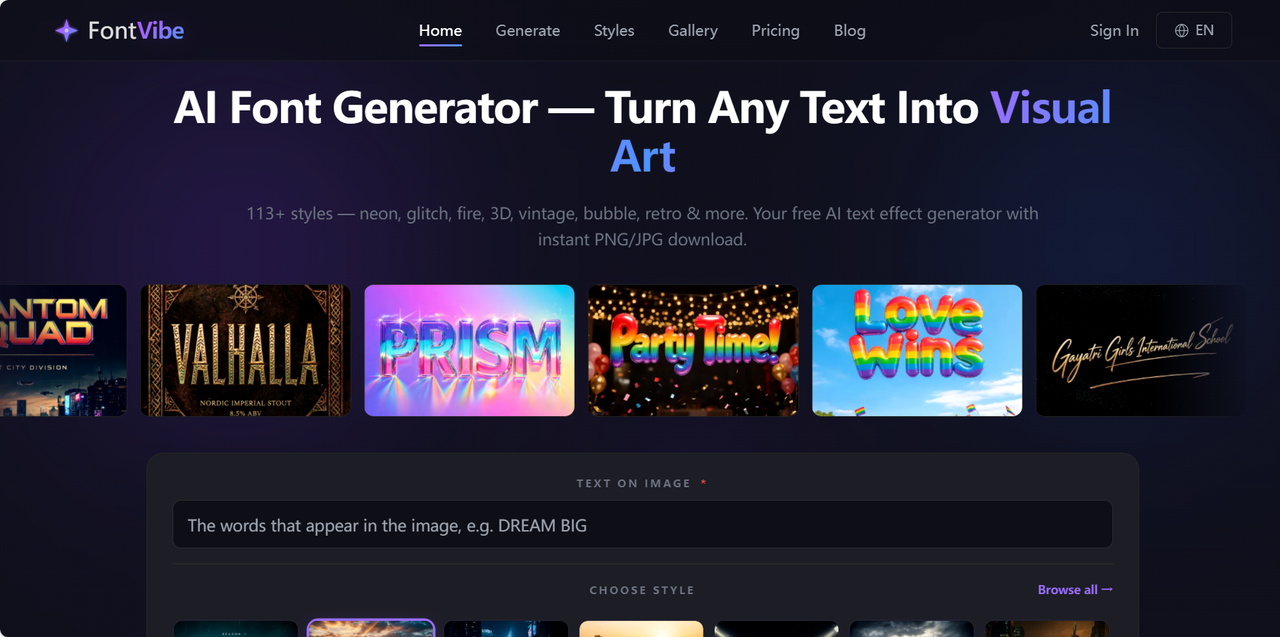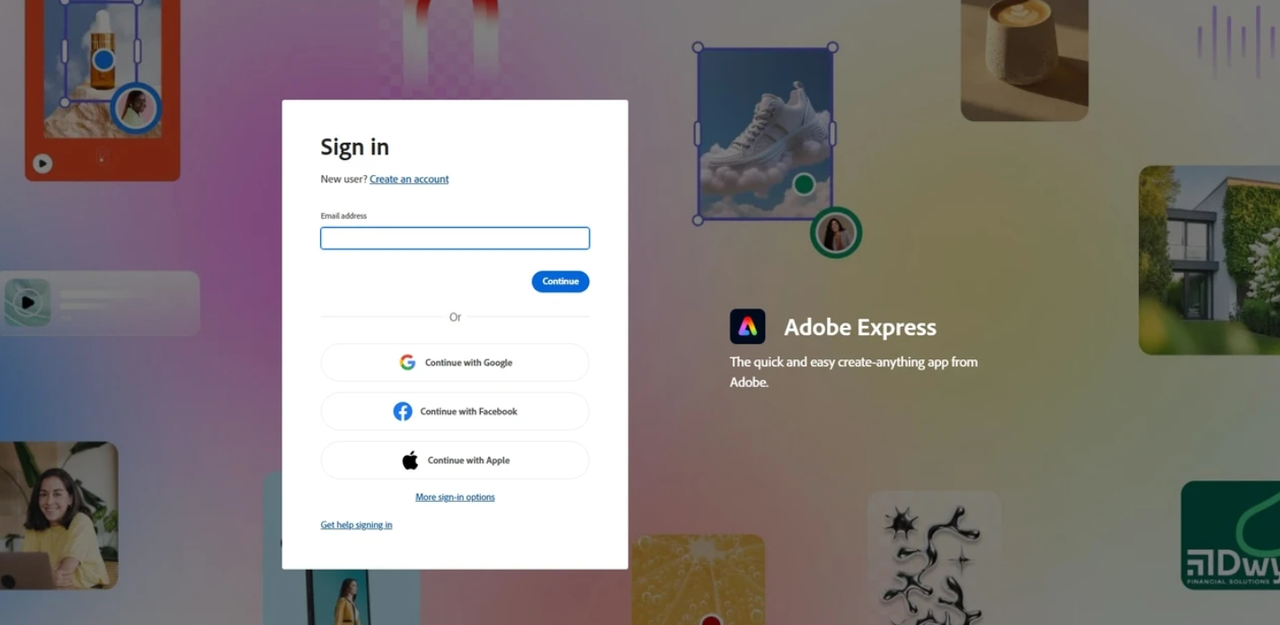
文字变艺术字怎么转?艺术字转换器大汇总
觉得自己选择的字体太过普通,想要把普通文字变成艺术字却不会用 Photoshop?别慌!如今市面上有不少好用的艺术字转换工具,无需设计基础,选择模板就可一键出图,完美适配海报、品牌、短视频封面、社交媒体配图等设计场景。艺术字不仅美观有趣、醒目张扬,而且用途广泛,选择一款适配的艺术字能一秒抓住观众的眼球。本文整理了 5 个优质的艺术字转换器,全程傻瓜式操作,帮你快速搞定各种创意艺术字需求,让文字瞬间出彩,让你的设计作品更加光彩夺目!
一、字由
字由是目前国内规模较大的字体管理工具,注册用户远超 2000 万,与汉仪字库、蒙纳字库等字体厂商有深度合作,同时作为腾讯、京东、小红书、国家电网、华为等国内头部大品牌合作伙伴,产品值得信赖。字由拥有海量字体资源,其中免费商用字体 3590+ 款,会员商用字体 590+ 款,授权方式灵活,满足多样化设计需求。用户只需要选择自己喜欢的艺术字资源,输入自定义文本内容,即可在线预览字体效果,实现普通文字到艺术字的转换。字由还在字体使用这方面进行了流程优化,通过字由客户端可实现在 PS、AI、ID、XD、Figma、Sketch、CDR 等设计软件中一键应用字体,无需下载安装字体包,即可完成字体应用。如果你觉得这些还不能满足你的需求,字由还提供 400+ 字体特效目标,包含电商,商务,科技感,新媒体等各类风格,用户可对特效文案,文字效果进行自定义编辑,打造一个更吸睛的艺术字效果,编辑后一键导出 PNG 图片,即可应用于作品中。
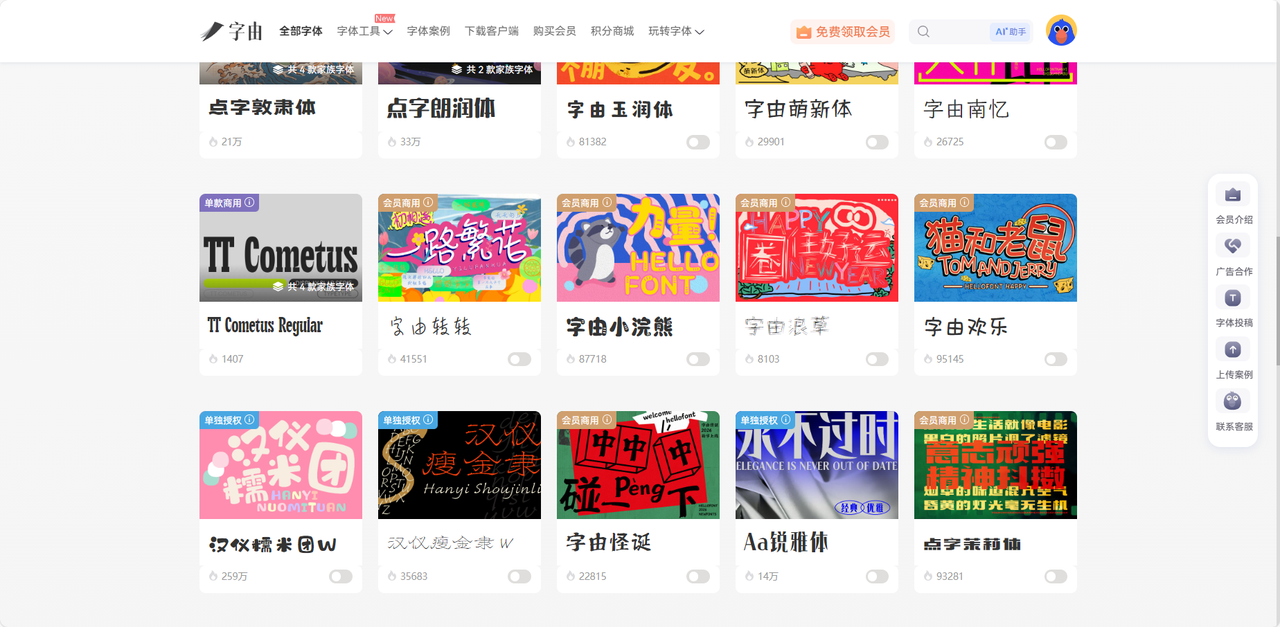
二、FontVibe
FontVibe 主要是给字体添加风格特效,比如霓虹、故障、火焰、赛博朋克等 100 多种文字视觉效果,让你的艺术字变得更加有视觉冲击力。操作流程非常简单,用户在输入框中输入自定义文案内容,从各种风格中挑选一个自己想要的,AI 会即刻完成自动渲染,导出高清或透明背景的 PNG 图片可直接用于其他设计软件。就整体的视觉效果来看,FontVibe 对于艺术字风格的质感控制相当智能,它不是单纯的在笔画边缘叠加一层光环,而是通过内置的 AI 系统将文字、光影、材质等细节完美适配,会让字体的呈现效果更加真实生动。
最近 FontVibe 还上线了一个新的字体风格,就是花卉植物类风格,也就是说你只需要输入一个名字,它会自动将植物元素(比如玫瑰、牡丹等)融入字体笔画内部,非常适合用来制作婚礼请柬、母亲节卡片、手作店品牌等,这种风格的艺术字会营造出温度感和亲和感更强的氛围。这个工具其实不太贵,而且我觉得免费版也足够能体验和艺术字相关的重点功能了,字体导出也没有水印限制,是个不可多得的艺术字转换器。
三、Adobe Express
Adobe Express 是由全球创意软件巨头 Adobe 开发,由 AI 驱动创意艺术字的生成,不是简单直接套用艺术字模板。进入 Adobe Express 之后,你要输入一些简短的提示词来描绘想要生成的艺术字风格,比如输入“金属立体材质的字体”,它会自动生成带有金属光泽和立体感极强的字体效果。或许你觉得转换完成的艺术字还不够完美,Adobe Express 支持在线进行字体微调,用户可以自由更改字体的一些细节参数,让字体更加流畅饱满。对于经常需要在移动端设计产品的用户来说,Adobe Express 也能满足你,它支持手机端创作字体并在线实时预览效果,走到哪都可以随时用!与传统的 AI 工具不同,它给你保留了一定的自由度,让用户可以在 AI 基础上添加一些自己的思考,二次编辑字体,打造富有个性的艺术字。
四、Cool Text
Cool Text 想必大家都非常熟悉,这是一款相当经典的艺术字转换器,打开网站就可以立刻制作高级感且绚丽多彩的艺术字。虽然它的界面布局简单,但内置的功能完全能够应对日常的设计需求,对于新手来说这也是比较容易上手的工具之一了。你可以自由选择喜欢的艺术字效果,进入编辑界面后调整尺寸、对齐方式、配色、文字内容,一切就搞定啦!它几乎没有任何复杂的功能,也不需要高难度的设计技巧,你在 Cool Text 可以专注于艺术字本身,花费最短的时间大幅提升文字美化效果,也正是因为这样,它也成为了很多国际设计师的在线字体美化神器。
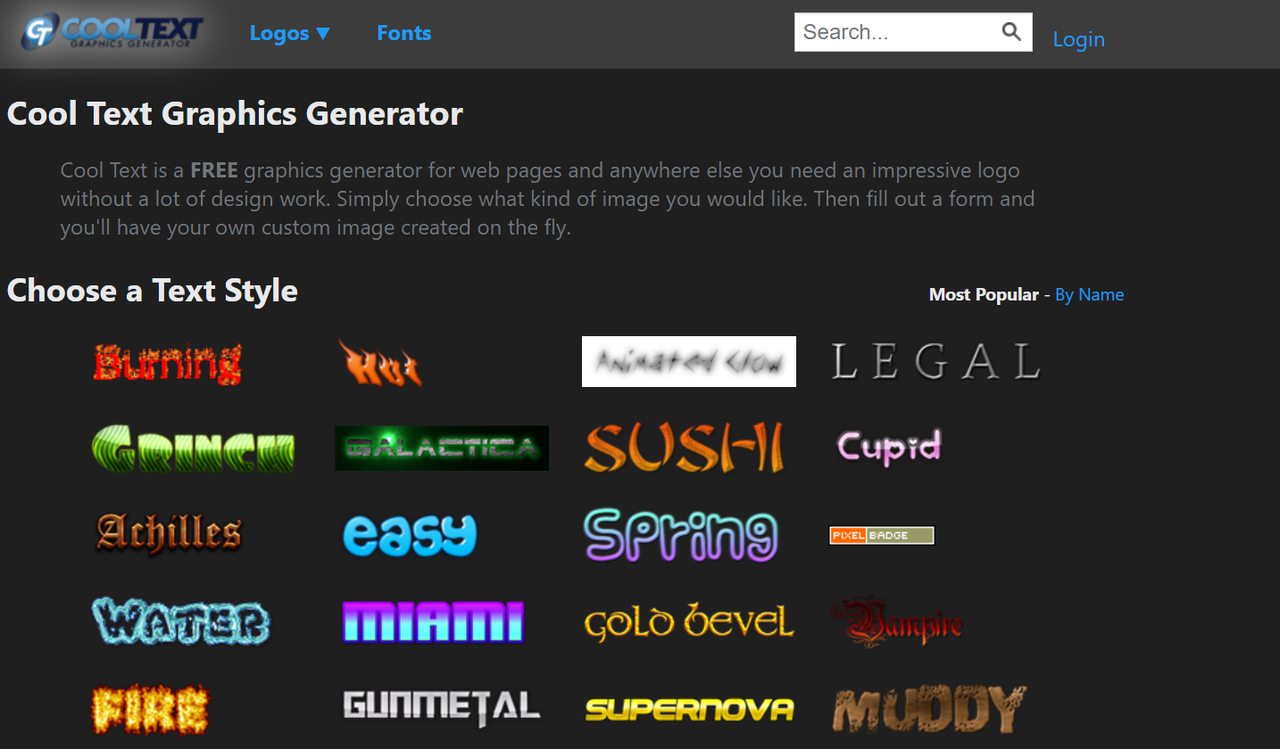
五、Font Meme
如果你是深耕于电影行业的设计师,那赶紧码住这个 Font Meme 吧!它最大的特色就是资源库包含了大量知名电影、电视剧、游戏、品牌的官方字体,你能想到的几乎都可以在这里直接预览生成对应的艺术字。最关键的是,它还提供了 50 多种 3D 文字特效以及上百种可以复制粘贴的字体风格,这些对于艺术字转换都是非常有帮助的,可以让你快速找到并生成满意的电影感艺术字。我还非常喜欢 Font Meme 的手绘花体字,可选择的样式真的超多,而且花体字效果贴近手写的真实质感,自然且逼真,放在你的设计作品里能大大提升整体质感,也能向观众传递出更细腻的情绪。
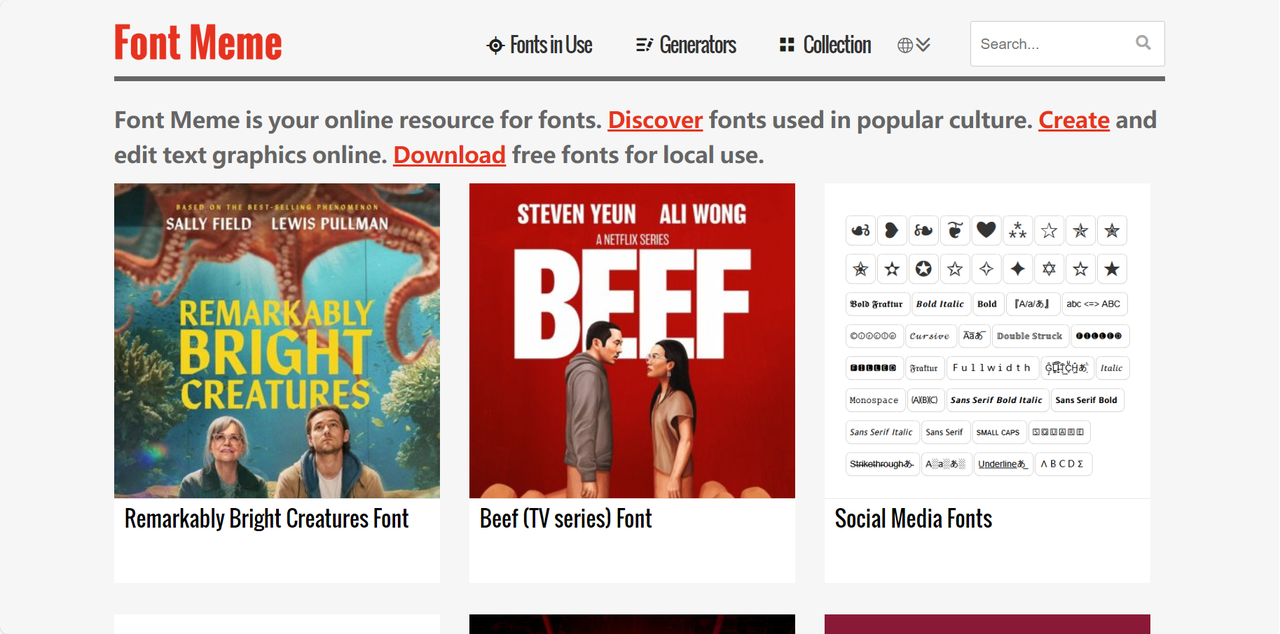
以上就是为大家整理的艺术字转换器大全,无论你就是想要做海报设计、品牌设计、影视设计,还是社交媒体配图、短视频封面等等,这些工具都能帮你一键实现文字转艺术字,轻松打造吸睛的创意效果。整体来说,字由是非常适合咱们国内设计师的一个字体工具,海量字体资源任你挑选,且授权清晰,完全让你用字无忧。每个艺术字转换器都有它独特的功能,根据你目前的设计需求以及使用场景,选择一个适合你的工具吧!轻松把平淡普通的文字转换成惊艳美观的艺术字,打造更高质的创意作品!